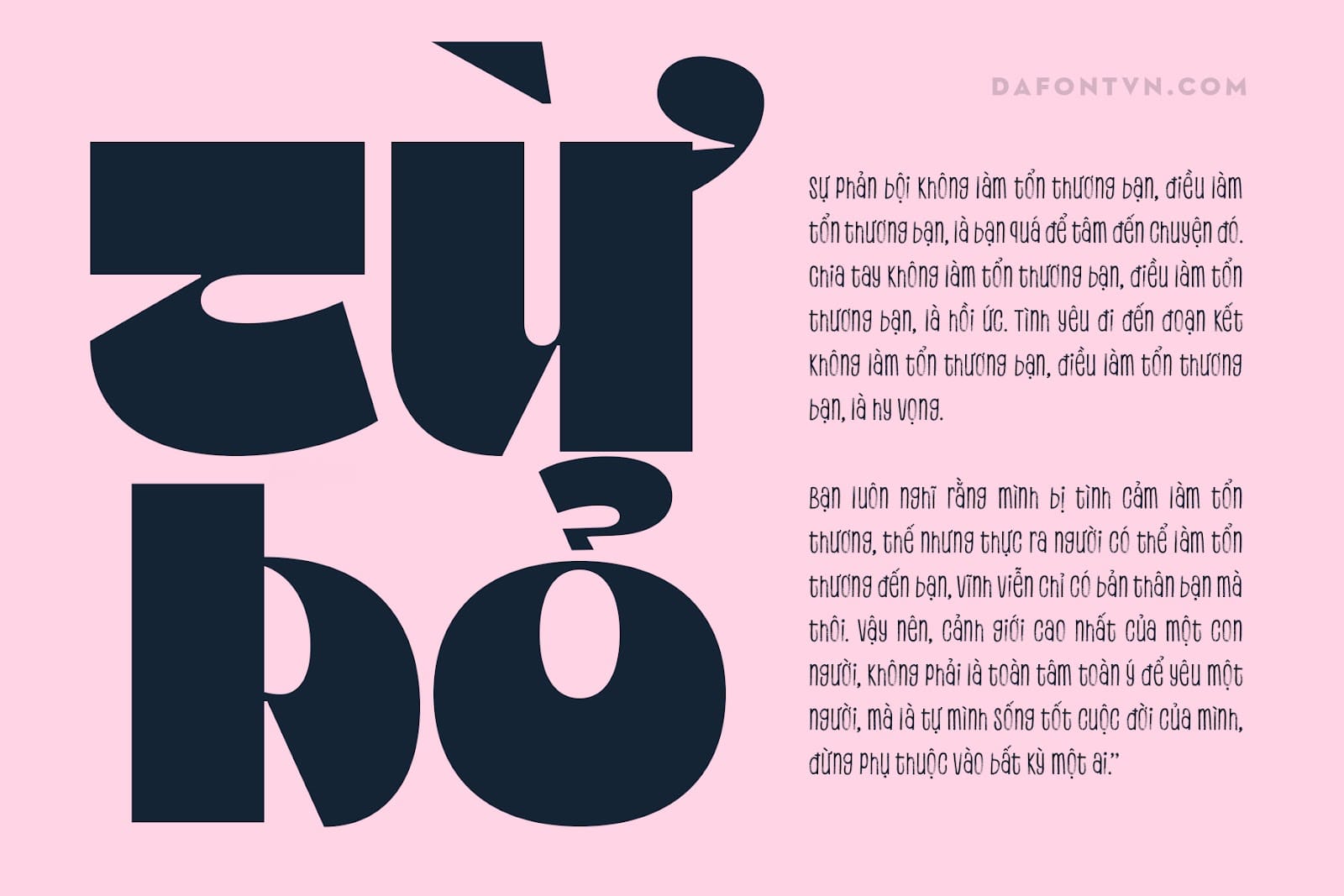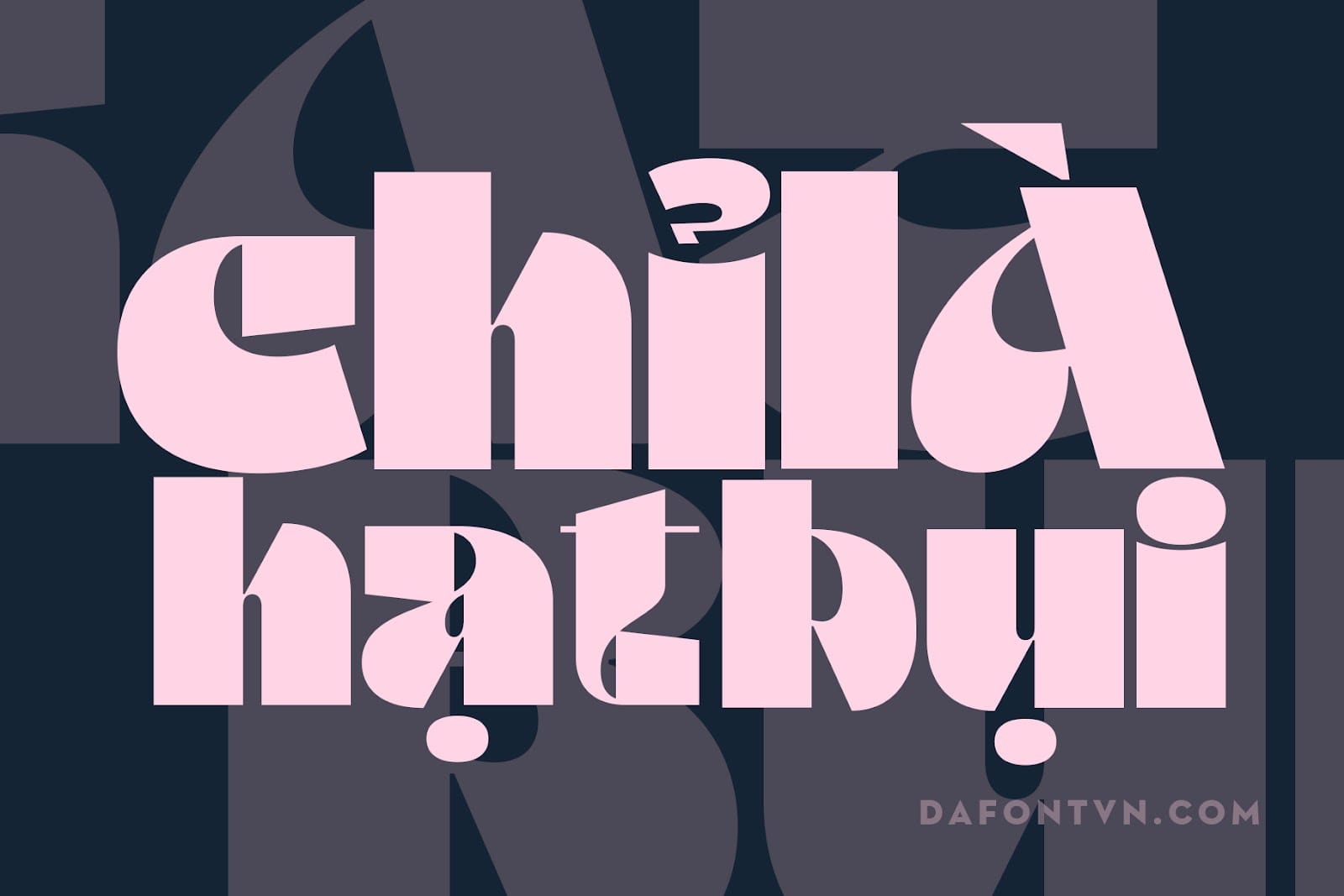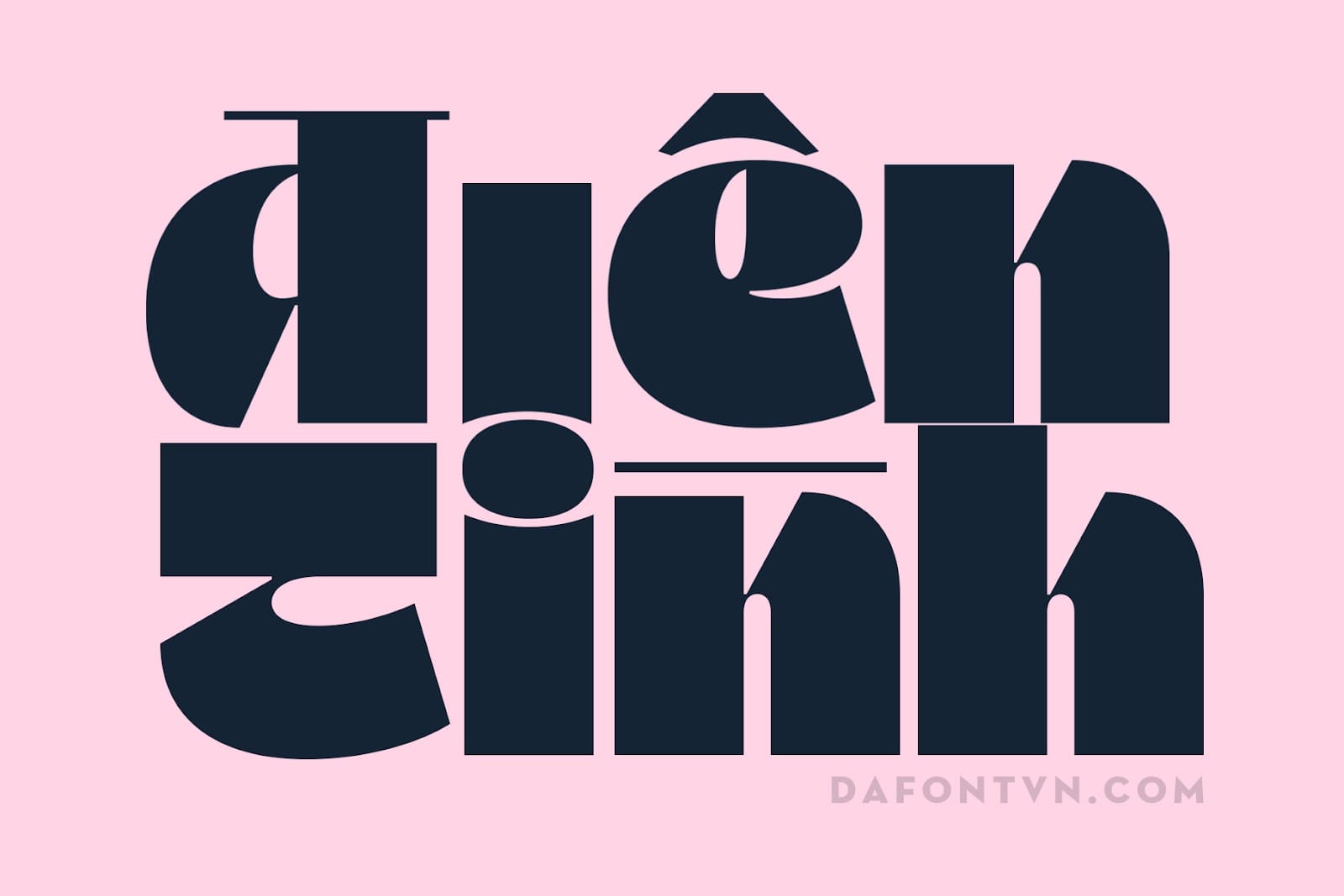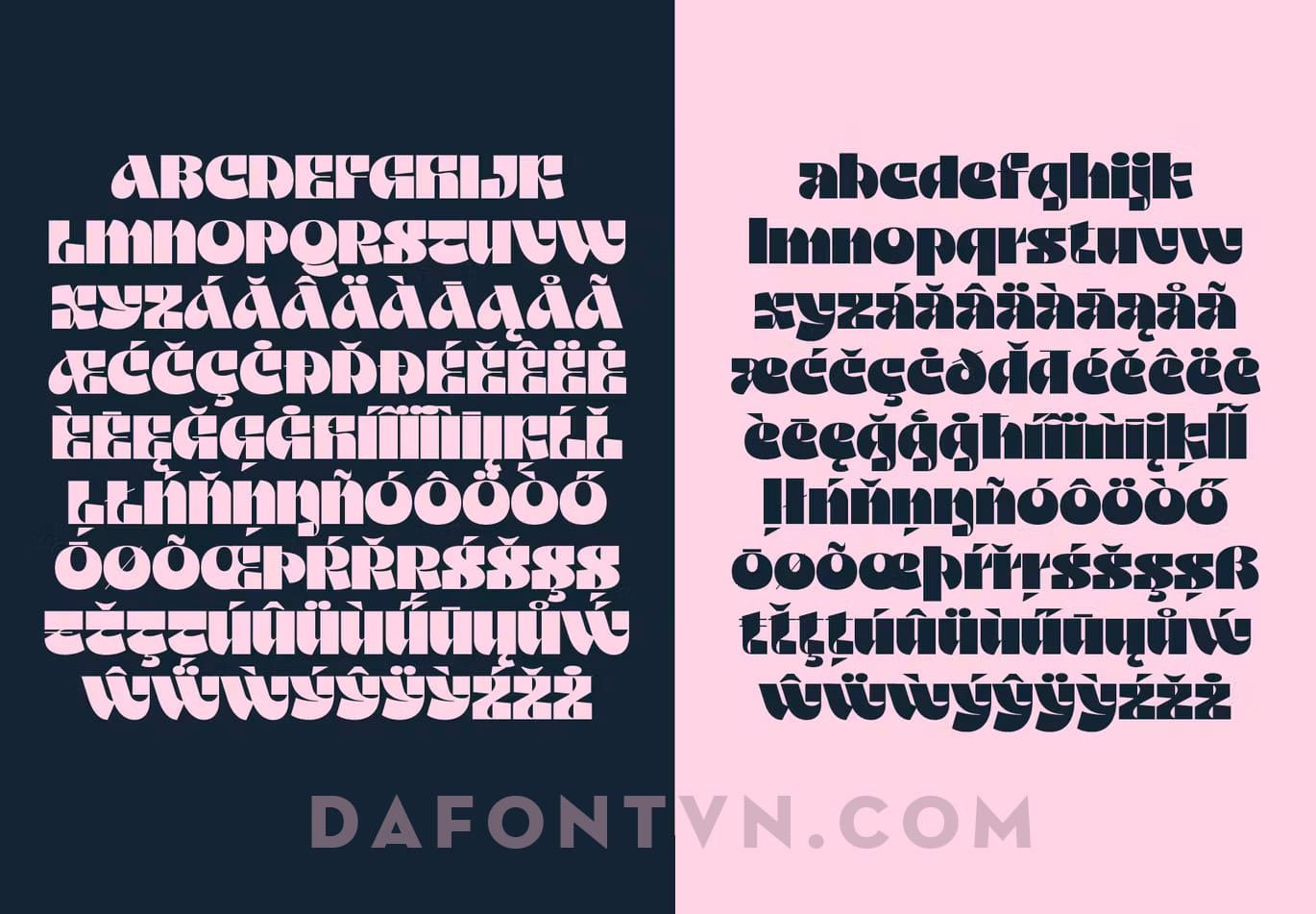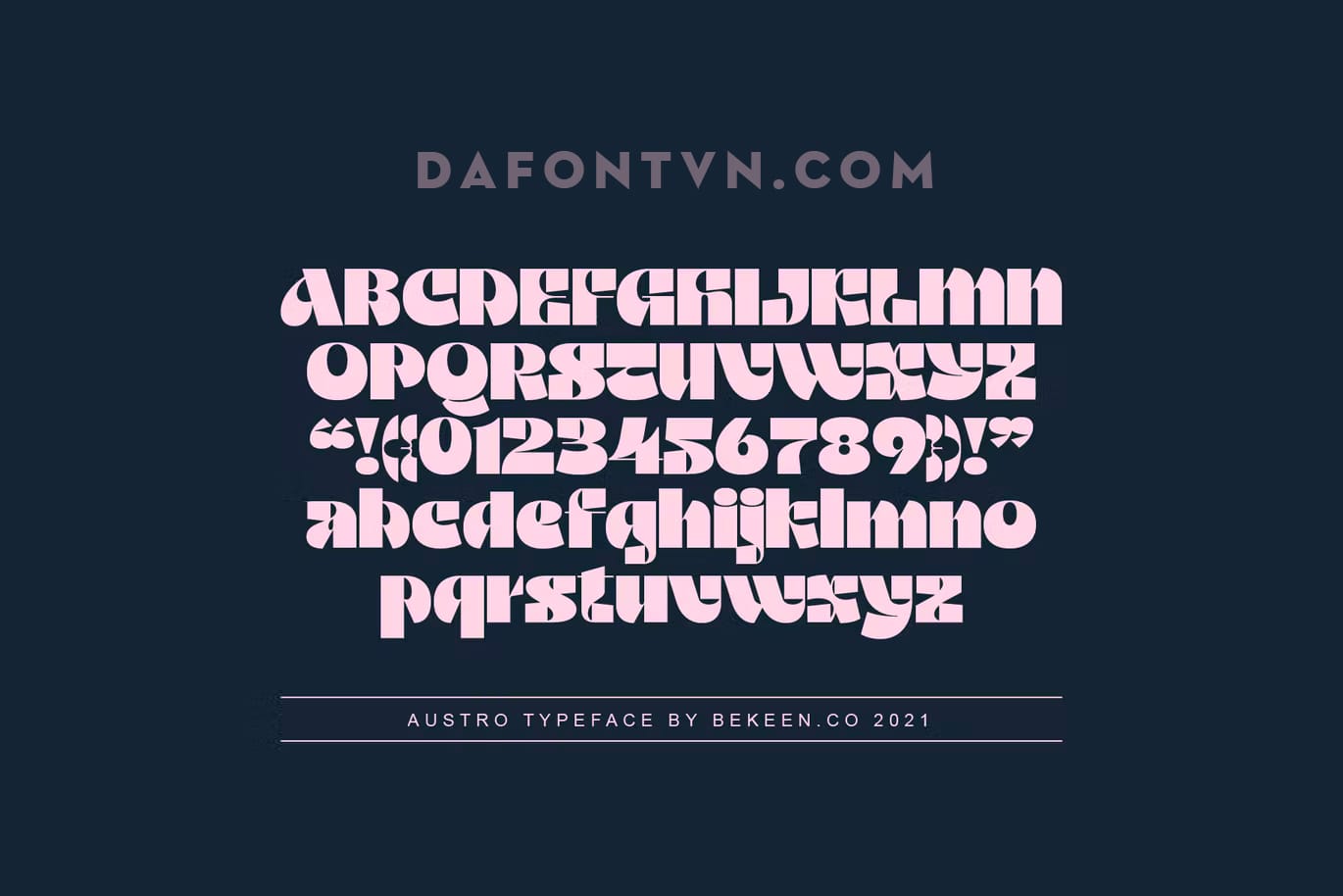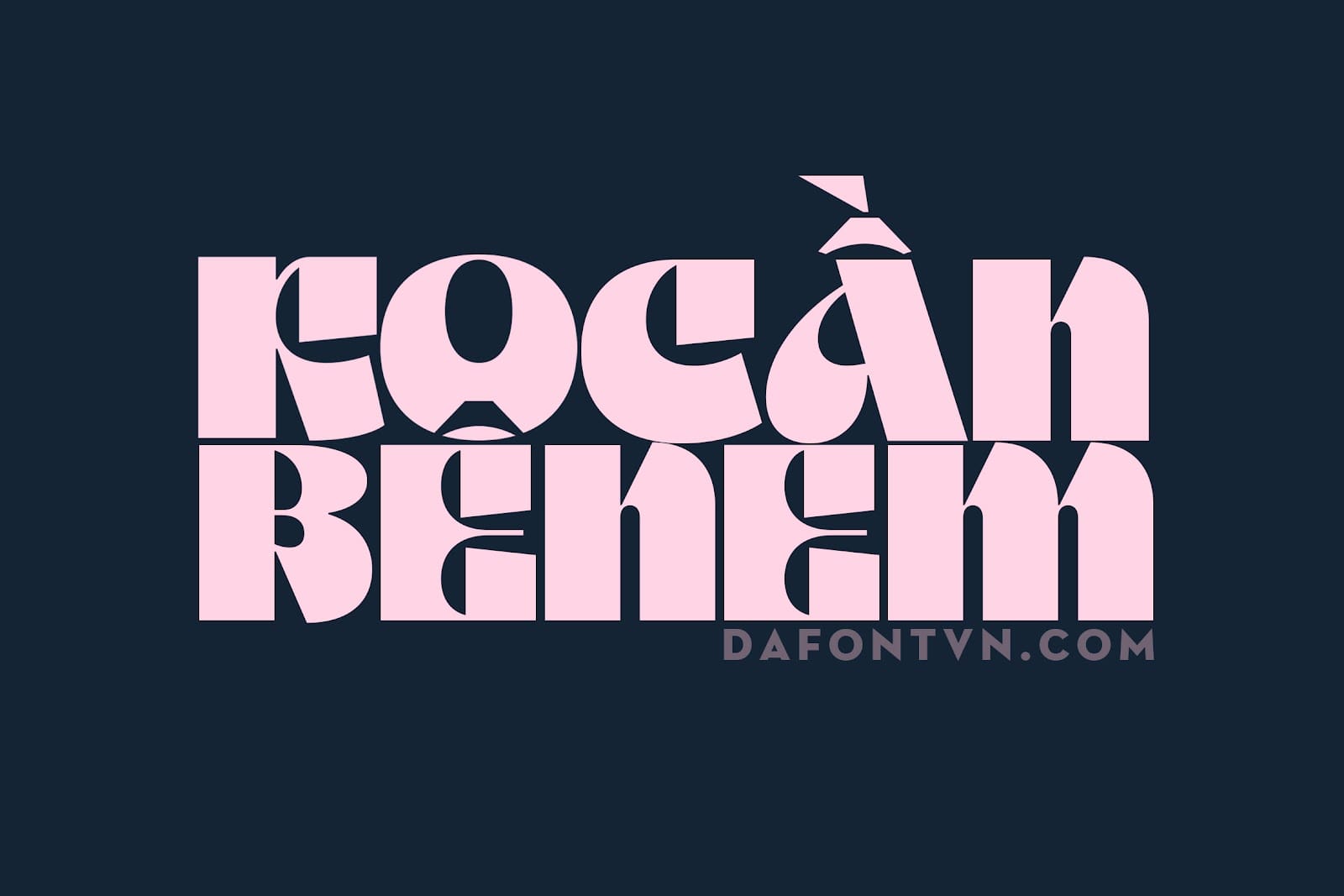
Font việt hóa Austro Typeface được lấy cảm hứng từ Motter Ombra ban đầu được thiết kể bởi Othmar Motter vào năm 1973. Austro Typeface mang đến sự mới mẻ hơn với một chút cổ điển và hiện đại, được thiết kế với các hình dạng hình học vì vậy phông chữ này hoàn hảo cho các thiết kế với các tiêu đề đòi hỏi to, rộng và một chút đặc biệt.Ngoài ra có thể sử dụng xây dựng thương hiệu, bao bì sản phẩm, trang trí hay cần 1 font chữ nổi bật. Font được việt hóa, kerning đầy đủ cũng như tối ưu và chỉnh sửa lại.